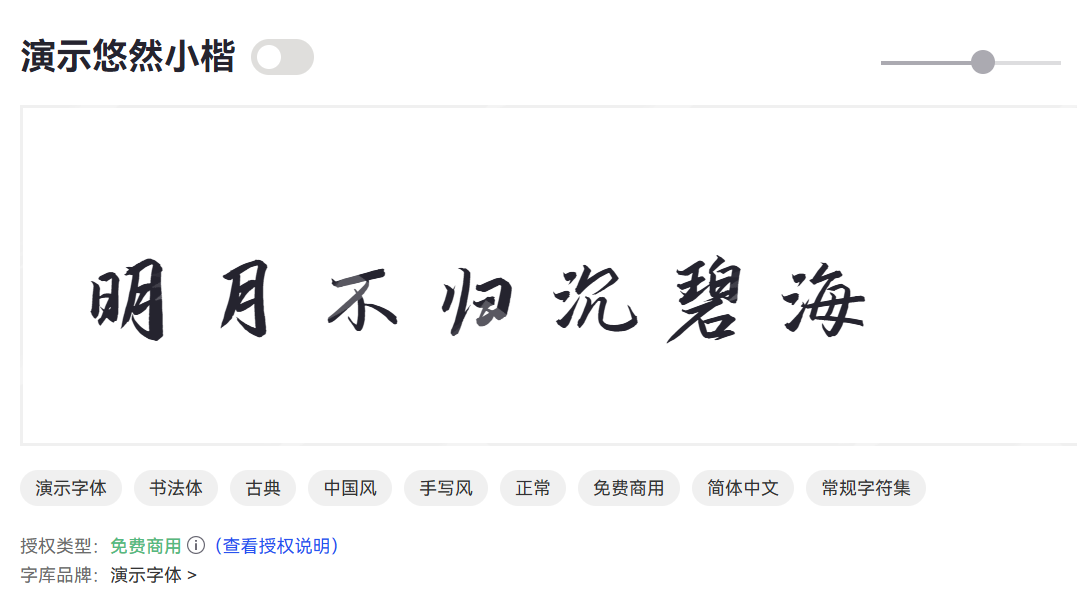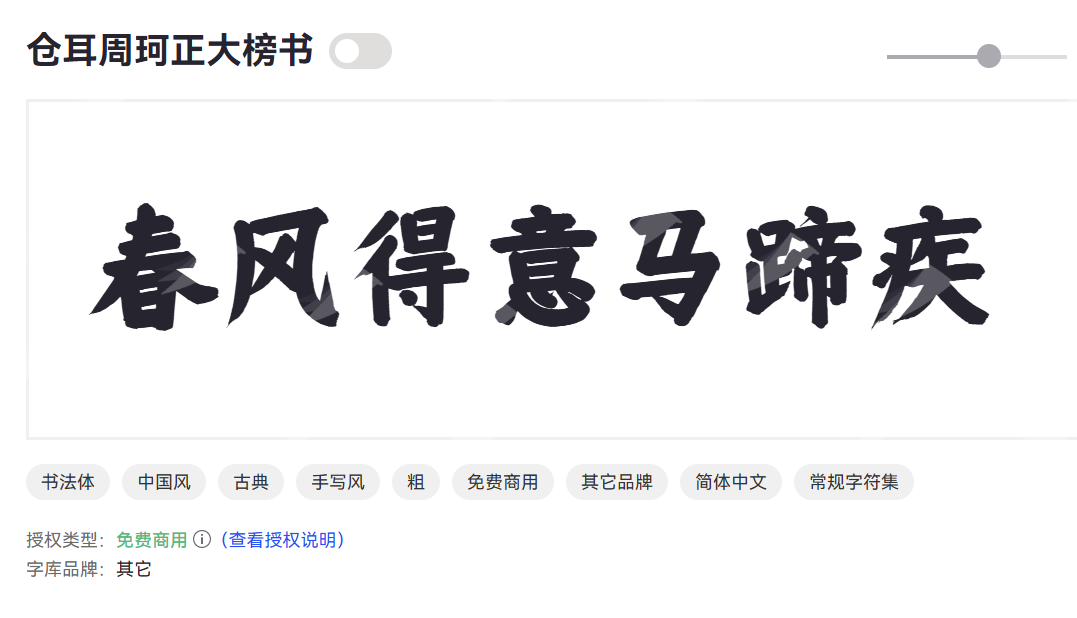
去哪下载免费商用的书法字体?一文告诉你完整攻略
很多朋友做设计、写文章、做海报或准备活动材料时,都希望能找到“免费可用”的书法字体,但市面上很多字体要收费,或者下载后要小心版权风险。我自己试用过不少,发现真正能放心免费商用的书法字体其实挺多的。
有了免费商用的书法字体,你可以:
- 轻松制作宣传海报、活动邀请函、书籍排版、网站界面或日常笔记,成本几乎为零。
- 选择自己喜欢的书法风格,比如古风楷书、飘逸行书、活泼手写体,瞬间让作品看起来更有艺术气息。
- 避免版权纠纷,安心商用或分享,不会因为字体问题影响设计效果。
5 款免费商用的书法字体
下面我分享我在使用字由时挑选的5款免费书法字体。这些都是经过筛选的,笔画真实。
演示悠然小楷
这款字体整体小巧精致,笔画微微连接,像毛笔书写时留下的自然“牵丝”。我用它来做小篇幅的活动手册或儿童活动卡片时,效果特别好,显得柔和亲切。缺点是字符较少,但核心常用汉字覆盖率高,下载后安装在电脑上,Word和PPT里都能完美显示。适合日常笔记或简短宣传语。
仓耳周珂正大榜书
榜书风格大气磅礴,笔画雄健有力,适合做大型海报或活动横幅。我试用时发现,它在PS里放大到2米海报上,文字依然清晰有力,不会变形。字由平台提供了在线预览功能,我可以先看效果再下载,超级方便。这款字体笔触真实,保留了传统榜书的庄严感,商用时放心大面积使用。
钟齐志莽行书
这款行书飘逸潇洒,笔画间有自然的连接感,写起来像书法家现场挥毫。我在做活动策划文案或节日贺卡时特别喜欢用它,整体效果轻松不失专业。安装后,在Illustrator里调粗调细都很顺手。字由的演示页面能直接看到不同文字组合,我下载前就确认了它覆盖率高,没有遗漏常用字。
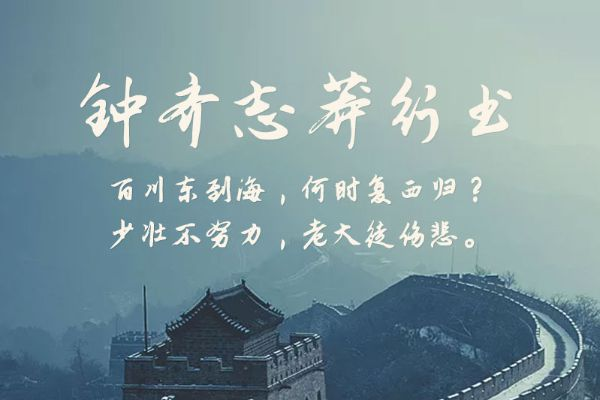
杨任东竹石体-Medium
竹石体风格清新自然,笔画如竹节般有节奏感,适合做家居装饰品设计或环保主题的海报。我用它来制作公司年终活动简报时,文字与背景结合后很有层次感。Medium版本的笔画适中,既稳重又不呆板,下载后可以在多种软件里切换颜色,效果出乎意料的好。
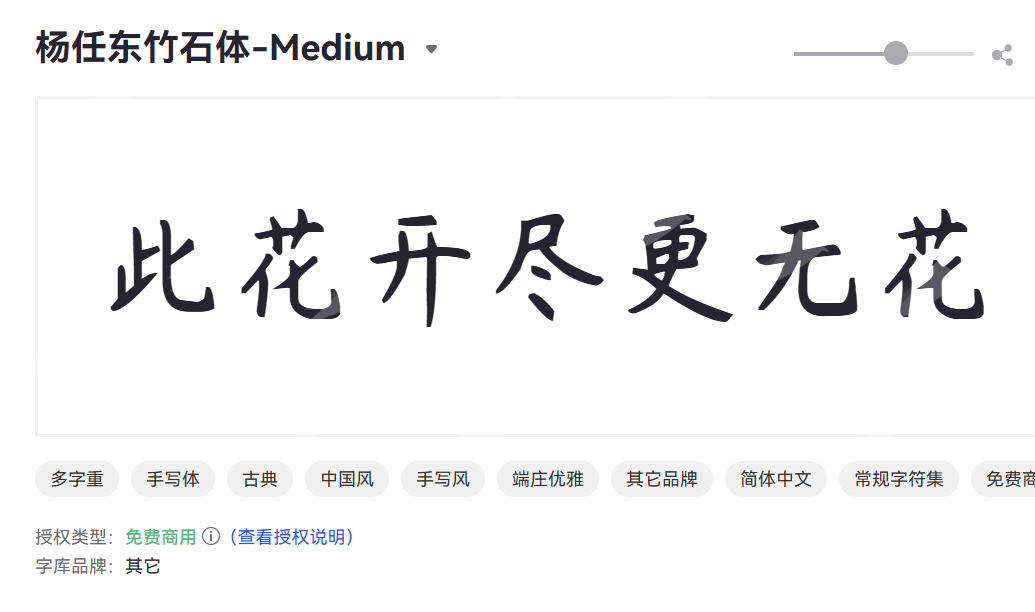
演示佛系体
佛系风格慢节奏,笔画圆润柔和,像禅意书法。我在追求平静感的设计时会优先选择它,比如做冥想主题的活动海报或健康类公众号排版。字体整体温暖友好,不张扬却有禅味。字由平台提供了多种演示角度,我试用后发现它在PPT投屏上也很清晰,商用时不需要额外改动。